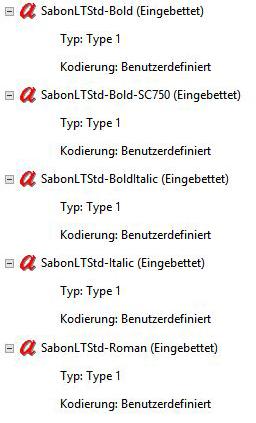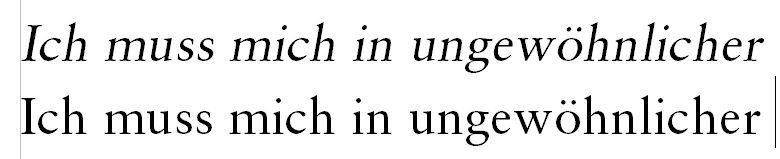
Typische Kursivschrift in Romanen
hm...wenn ich im Writer die Sabon kursiv setze, dann sieht das so aus. Das heißt die Sabon in Kursiv müsste man sich extra besorgen? Ist das dann bloß so ein Default-Setting in Open Office, dass die Schrift einfach neigt? Wenn das so ist, war das eine peinliche Frage von mir, sorry :)
Kein Problem, so etwas lernt man ja nicht in der Schule. Und es gibt ja auch Schriften, bei denen die Kursive nicht viel mehr als eine schräg gestellte Variante des geraden Schnitts ist (die heißen dann manchmal auch nicht Kursive oder Italic, sondern Oblique). Und nicht bei allen Kursiven unterscheiden sich einzelne Buchstaben (z.B. a, f, g, r) nicht nur durch die Neigung, sondern auch von der gesamten Buchstabenform her so deutlich vom geraden Schnitt wie bei der Times New Roman, Garamond, Sabon usw.
wenn ich im Writer die Sabon kursiv setze, dann sieht das so aus. Das heißt die Sabon in Kursiv müsste man sich extra besorgen?
Ja. Das gilt für nahezu alle Fonts. Es wäre zwar technisch gar kein Problem, alle Schnitte einer Schriftfamilie in denselben Font zu packen, aber dann wären sie nicht über den Kursiv- oder Fett-Schalter oder das Schriften-Menü der Benutzeroberfläche von OpenOffice o. ä. erreichbar, sondern durch die Aktivierung von OT-Layout-Features, die dann zwingend für die Funktionen Italic, Bold, Light u. s. w. einprogrammiert werden müssten.
Du solltest außerdem auch bei erfolgreicher Installation aller Schnitte einer Font-Familie in jeder Anwendung, in der du die Fonts nutzen willst, überprüfen, wie du die Schnitte über die Menüs erreichst und ob z. B. bei Aktivierung des Kursiv-Schalters tatsächlich der kursive Schnitt angezeigt wird. Die Schriftschnitte werden nämlich erstens innerhalb der Fonts, also der Software, miteianander verlinkt, wobei das nur mit maximal vier Schriftschnitten einer aus Regular, Italic, Bold und Bold Italic bestehenden Unterfamilie technisch machbar ist. Wenn eine Schriftfamilie aus sechs Schnitten besteht, nämlich Regular, Semibold und Bold und den entsprechenden kursiven Schnitten, dann verknüpfen die Schriftenentwickler meist Regular mit Bold, obwohl zur Auszeichnung einer Textstelle eher Semibold geeignet wäre. Semibold erreichst du dann also in Office-Anwendungen nicht über den Bold-Schalter, sondern über das Font-Menü. In diesem Zusammenhang muss dir auch klar sein, dass insbesondere kleinere Foundries in Bezug auf die Verknüpfungen und die internen Namen ihrer Fonts oft Fehler machen. Du kannst dich also nicht blind darauf verlassen, dass alle Schriftschnitte erwartungsgemäß über das Menü der Anwendungen erreichbar sind.
Wenn das so ist, war das eine peinliche Frage von mir, sorry :)
Peinlich ist das zwar nicht, aber in Bezug auf deine Erfahrung aufschlussreich. Wenn du ein Buch in der Verdigris gesetzt und dabei die falsche Kursive zur Auszeichnung verwendet hättest – das wäre peinlich gewesen. Also stell lieber Fragen, die dir peinlich sind, als aus Angst vor dummen Antworten, Bockmist zu produzieren.
Und es gibt ja auch Schriften, bei denen die Kursive nicht viel mehr als eine schräg gestellte Variante des geraden Schnitts ist
Die DTL Romulus scheint gar nicht mehr erhältlich zu sein. Die hatte eine falsche Kursive, weil die ursprüngliche Romulus auch eine hatte. So hatte DTL argumentiert, wenn ich mich recht erinnere. Das Ergebnis war katastrophal.